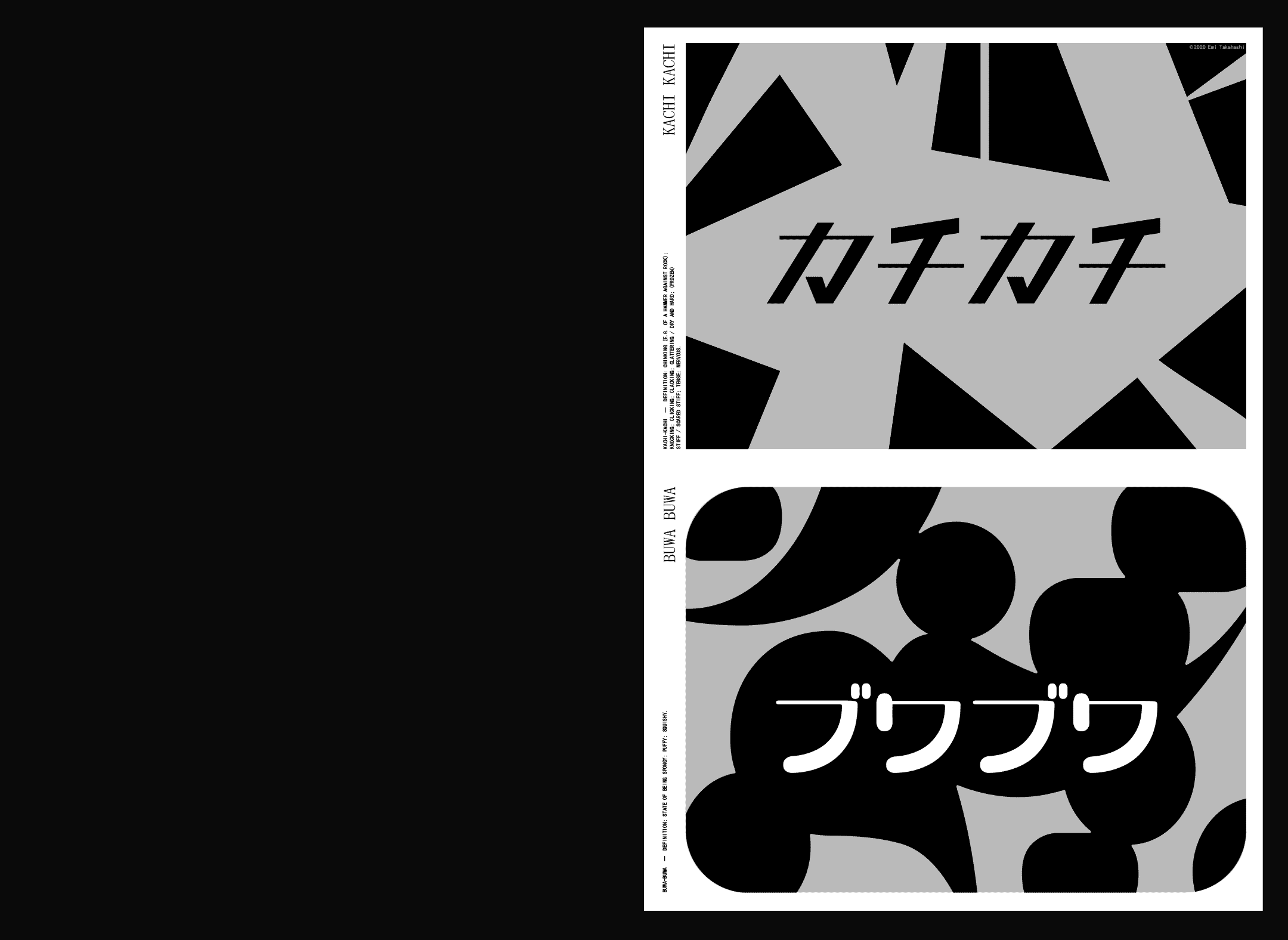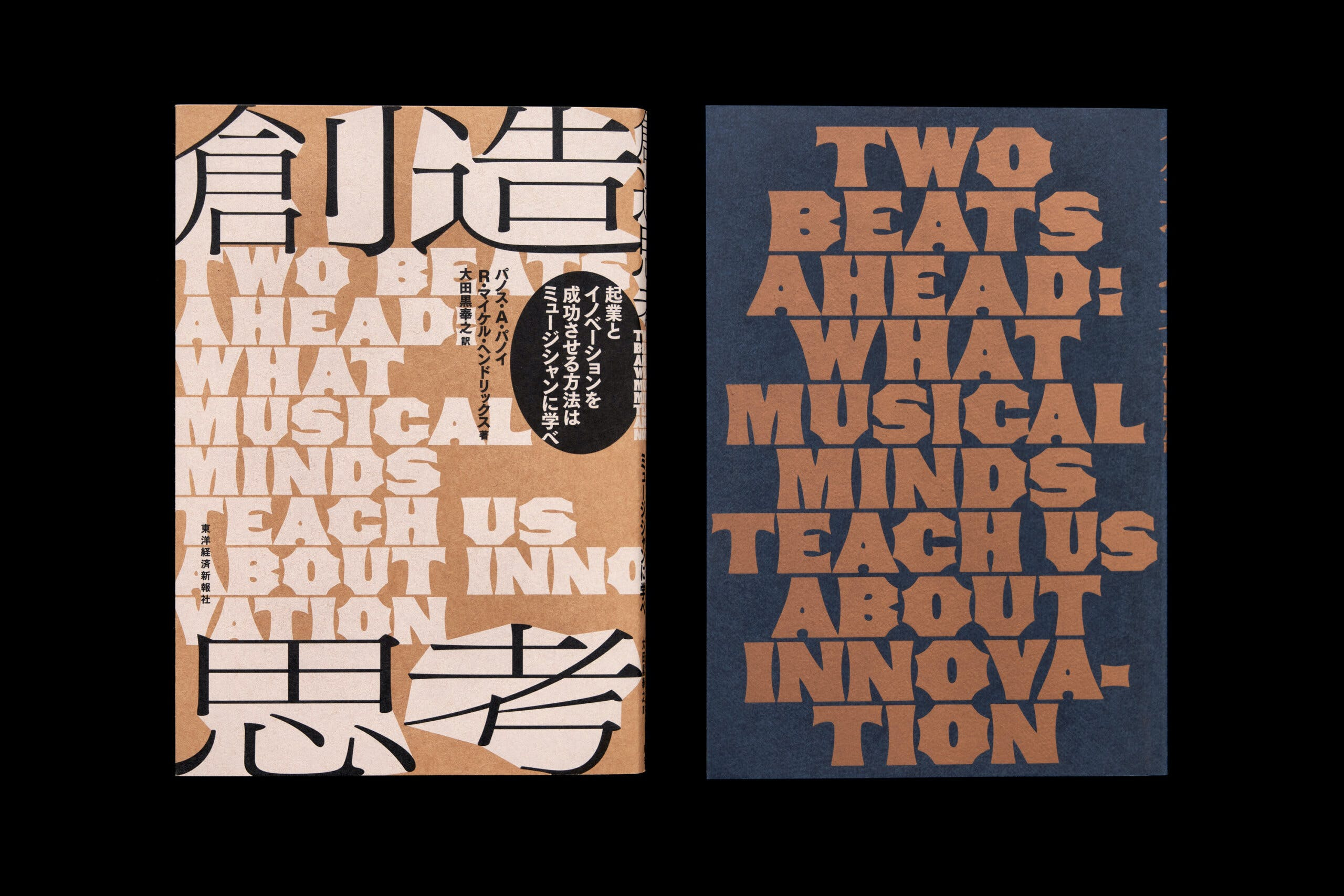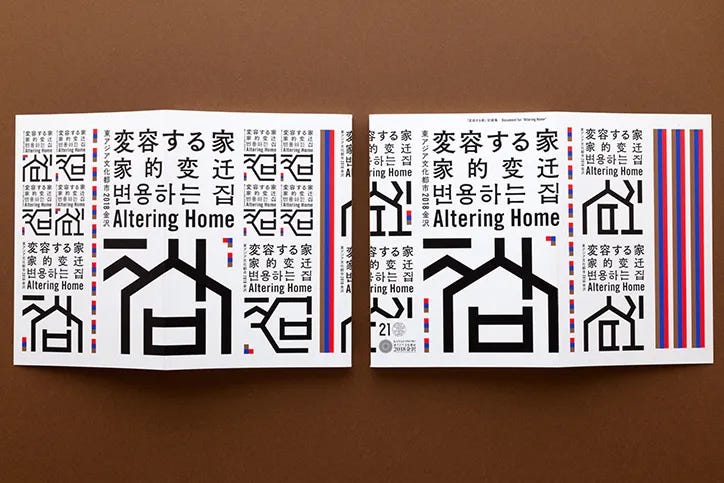
#11 [especial] tipografia pelo mundo: Japão [2]
hello! essa é a segunda parte da edição tipografia pelo mundo: Japão. essas edições são parte da primeira série de edições temáticas da makers gonna make, que surgiu da curiosidade sobre como funciona a tipografia em países com outros sistemas de escrita. na primeira parte eu falei sobre o sistema de escrita japonês, sua estrutura, história e os principais estilos tipográficos do país. hoje, como prometido na semana passada, vou compartilhar o trabalho de alguns designers e estúdios japoneses com foco em tipografia. espero que você curta :)
Tipógrafos e estúdios de tipografia do Japão
Agora que já entendemos a história e a estrutura da tipografia no Japão, nada mais justo do que conhecer o trabalho de estúdios e designers com foco em tipografia no país, certo? Se prepara, porque hoje vamos ter vários links de inspiração!
Estúdio Monotype
O designer Akira Kobayashi é um dos Diretores Criativos do Monotype, e sua experiência de mais de 30 anos na área tipográfica garante que as tipografias com suporte para o sistema japonês sejam incríveis. Eles trabalham bastante a integração entre os diferentes idiomas, e também criam fontes para o alfabeto latino.
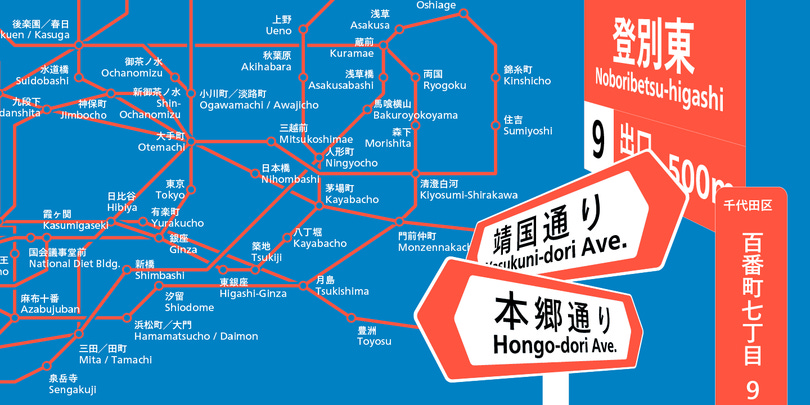
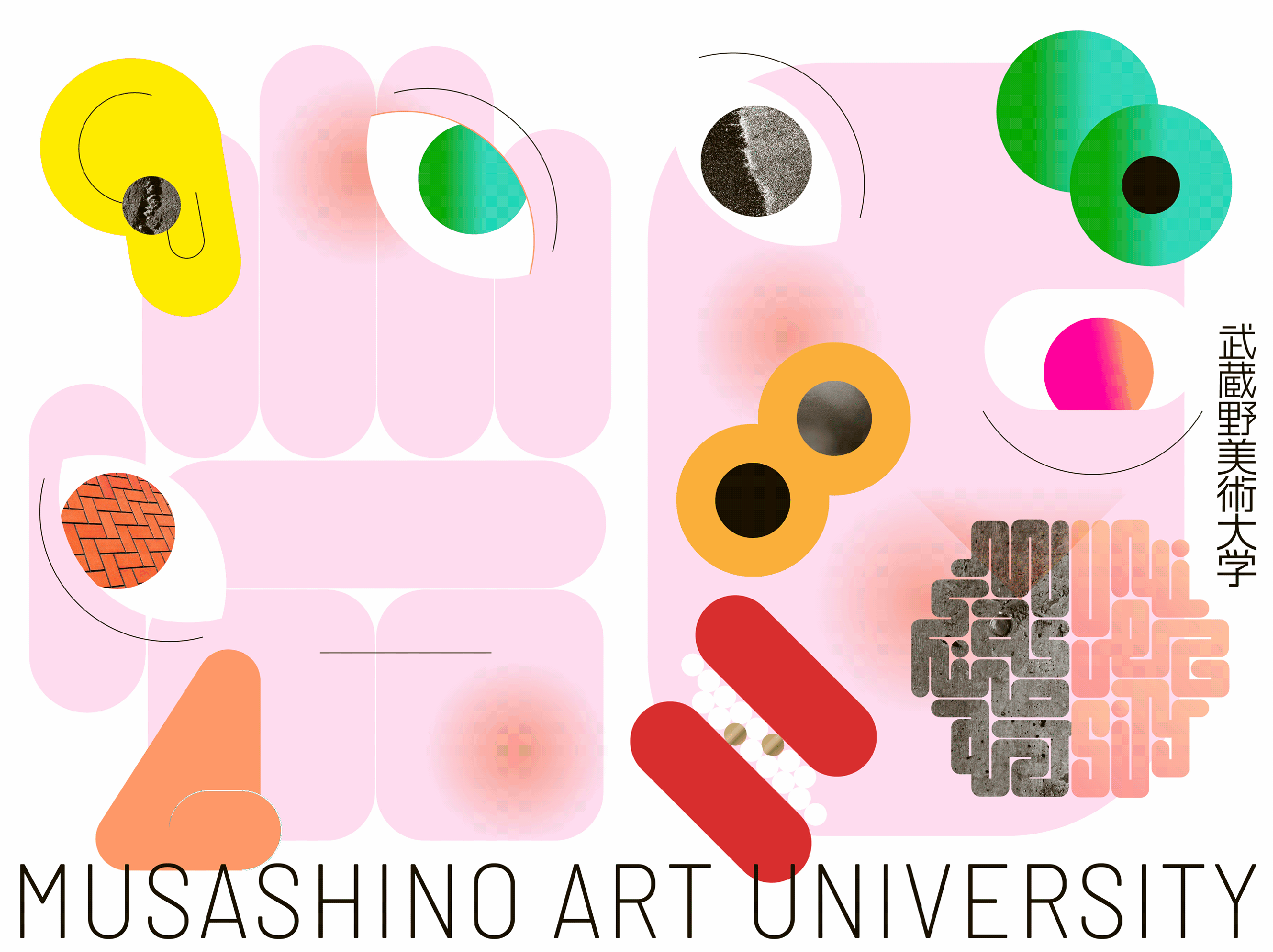
LABORATORIES / ラボラトリーズ
Embora eles não criem fontes, o design tipográfico está no centro do universo criativo desse estúdio de Tokyo. Os designs são mais dinâmicos e misturados, com a exploração de diferentes sentidos de leitura até para os caracteres latinos. Gosto especialmente do uso de caracteres como ilustração.
Emi Takahashi
Emi é uma designer e artista canadense-japonesa e seu trabalho não se limita ao design de tipos. Mas ela desenvolveu a incrível Kachi-Buwa, uma fonte para trabalhar a expressão de onomatopeias. A tipografia conta com variações mais pontudas e mais arredondadas, baseadas no efeito “kiki ou bouba”. E no site da Kachi-Buwa dá pra ver todos os seus “extremos”.
Design de posters tipográficos
A designer Katya Tinmey, uma fã de posters tipográfico japoneses, escreveu um artigo em seu medium onde ela apresenta diferentes posters e tipos de composição: texto como ilustração, falta de espaço negativo, mistura de linguagens diferentes.. Vale a pena conferir a seleção que ela fez e detalhou :)
Em 2019 o Google Fonts tinha menos de 10 tipografias com suporte para o idioma japonês na sua biblioteca; mas decidiram mudar isso, como mostra esse artigo do blog deles. Hoje, são mais de 50 famílias de fontes, um aumento significativo. Uma vantagem do Google Fonts é conhecer os designers/estúdios responsáveis pelas criações e ter acesso ao download gratuito de famílias inteiras :)
💭 como funciona a tipografia japonesa?
Entender o funcionamento da tipografia no sistema de escrita japonês pode tornar a apreciação dessa área do design muito mais rica. Eu escrevi sobre isso na edição passada!